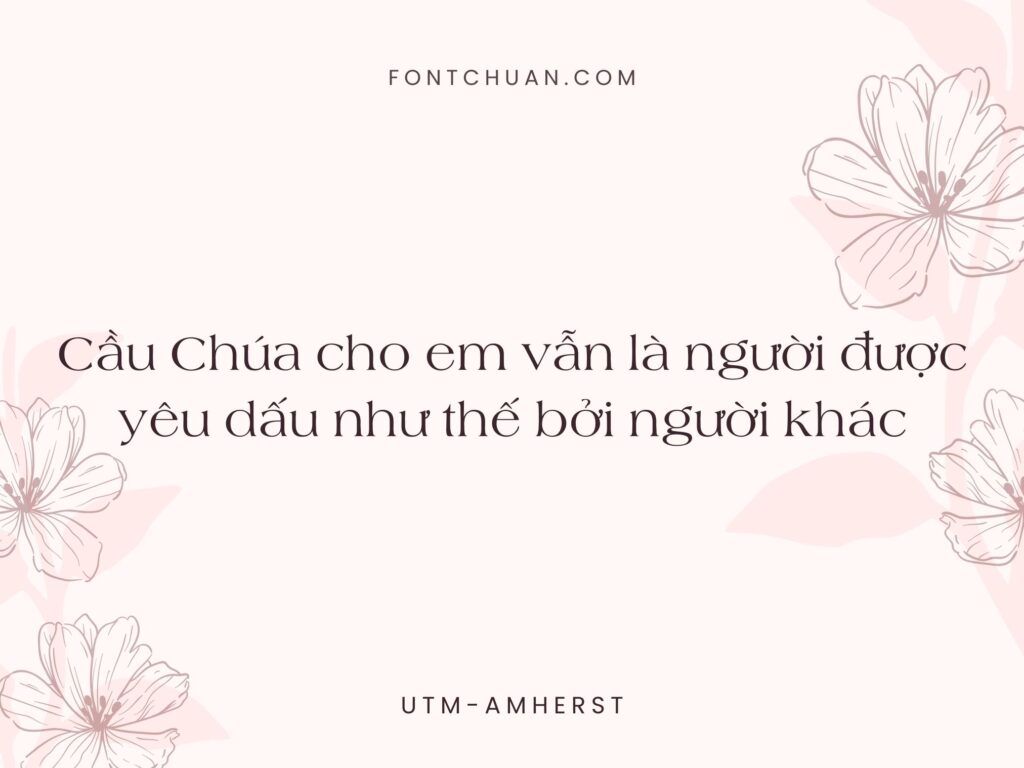
Font UTM Amherst Việt Hóa
UTM Amherst là một kiểu chữ serif cổ điển được phát triển bởi Công ty TNHH Vitoen. Font mang phong cách truyền thống, thanh lịch và dễ đọc, phù hợp với nhiều mục đích trình bày trang trọng và chuyên nghiệp. Phiên bản Việt hóa được thực hiện bởi Đinh Kiên, hỗ trợ đầy đủ tiếng Việt cùng hơn 200 ngôn ngữ khác. Đây là một trong những font được thành viên Font Chuẩn sưu tầm và chọn lọc để phục vụ cộng đồng thiết kế trong các dự án yêu cầu tính nghiêm túc và rõ ràng về thị giác.
UTM Amherst có cấu trúc chữ cân đối, với các nét thanh mảnh, chân chữ mềm mại và độ tương phản rõ ràng giữa nét thanh và nét đậm. Font đặc biệt phù hợp cho các thiết kế sách, tạp chí, tiêu đề chuyên đề, tài liệu in ấn hoặc nhận diện thương hiệu trong các ngành nghiêm túc. Những lĩnh vực như giáo dục, quảng cáo, công nghệ và bất động sản có thể ứng dụng Amherst để tạo ấn tượng chỉnh chu, lịch sự và chuyên nghiệp trong thiết kế.